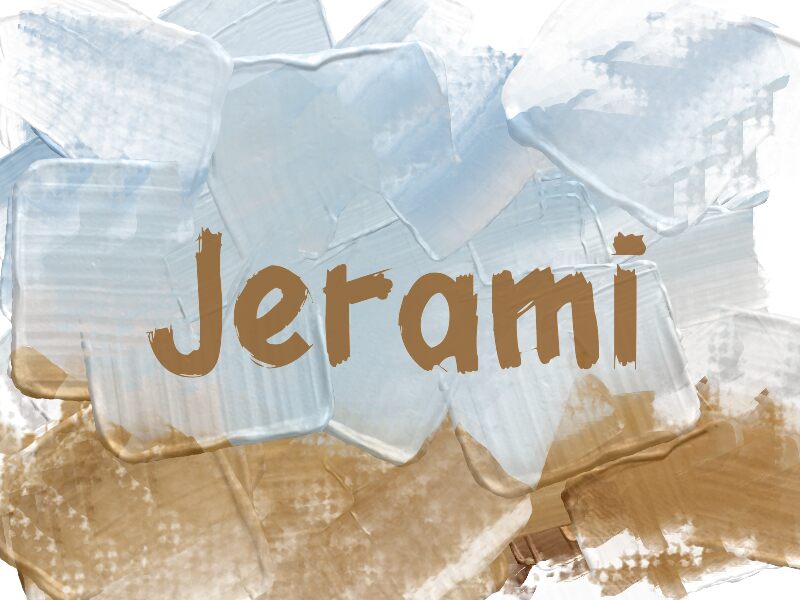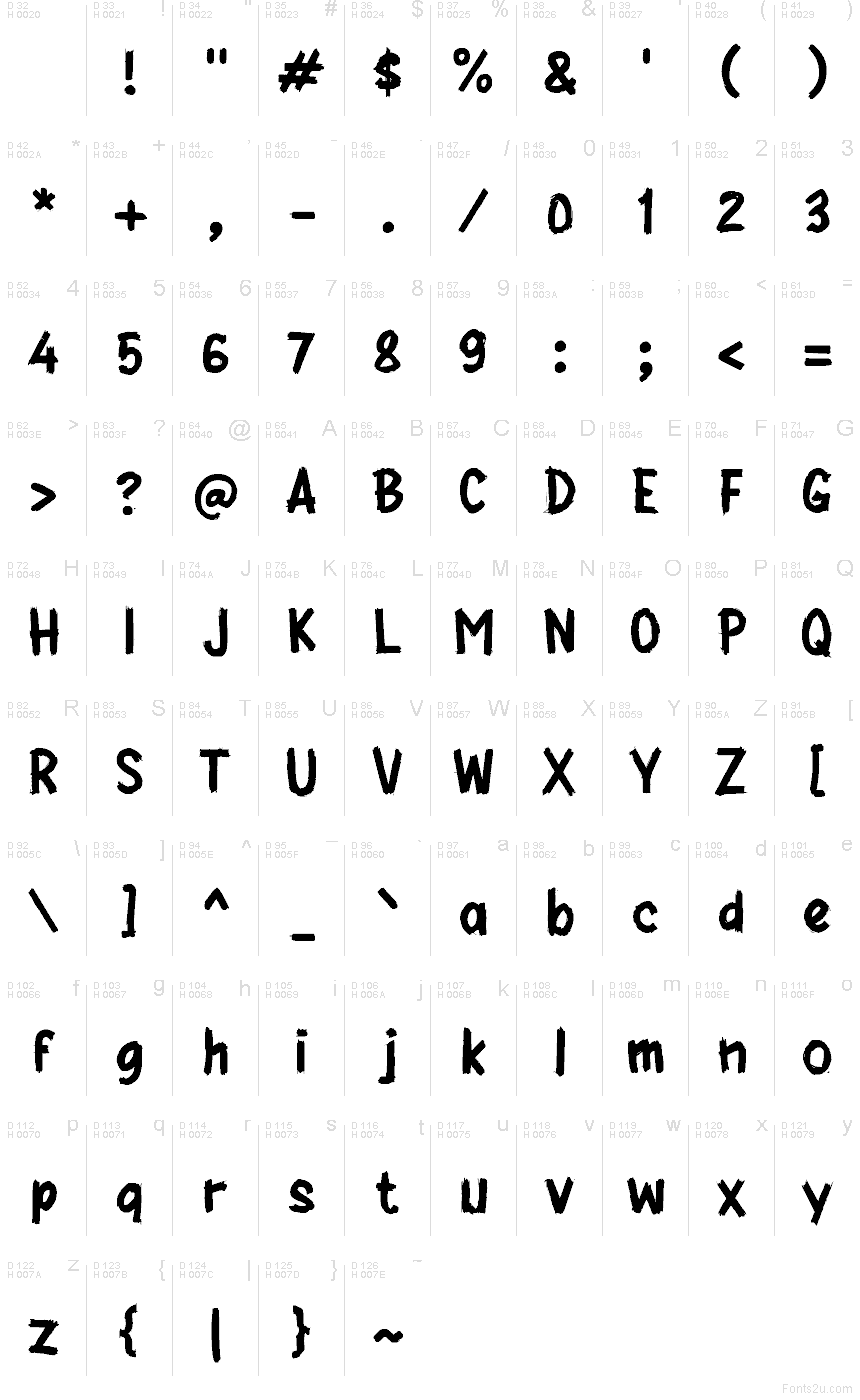
Jerami от Wep — это бесплатный «trash brush» шрифт с резким, рваным ритмом, создающий впечатление, будто он выцарапан прямо на бумаге. Буквы здесь толстые, беспокойные и неровные: с грубыми срезами, проплешинами от сухой кисти и живым, ручным начертанием, которое сохраняет сырой, нешлифованный вид.
Он идеально подходит для музыкальных плакатов, обложек зинов, стритвир-графики, титров и смелых заголовков в соцсетях, где от бесплатного шрифта требуется характер, а не аккуратность. Используйте его для коротких фраз, имён артистов или крупных цитат — рваная текстура кисти придаёт даже самым простым словам дерзкую, живую выразительность.
Jerami